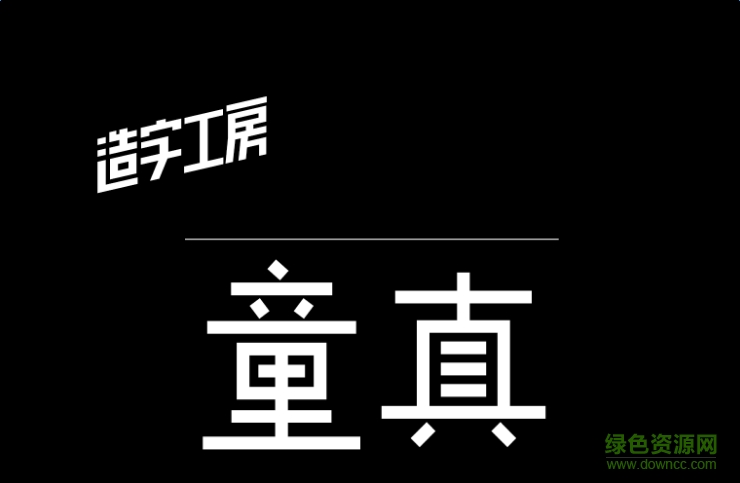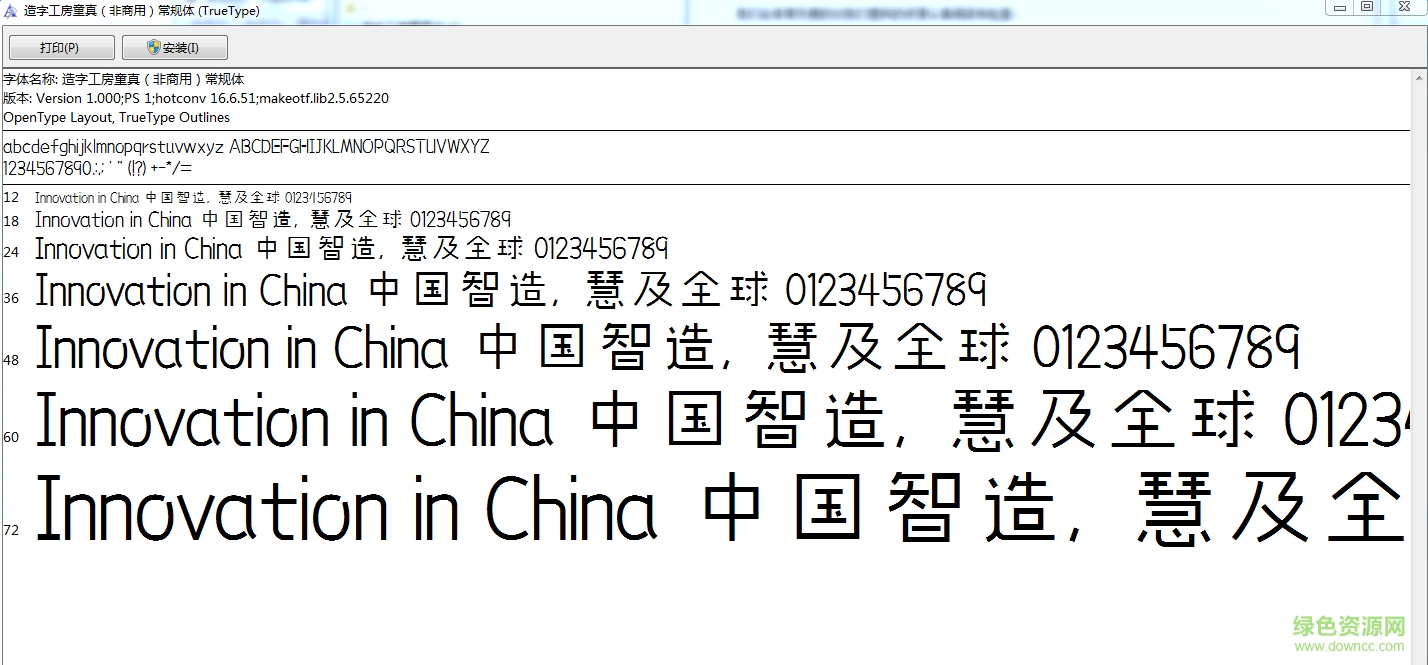
造字工房童真體是一款造字工房類可愛童趣風(fēng)格字體軟件,童真體整體效果無拘無束,非常的滑稽,在兒童讀物設(shè)計(jì)方面有著不錯(cuò)的應(yīng)用,歡迎到綠色資源網(wǎng)下載體驗(yàn),還有更多好看字體盡情期待!
造字工房童真體橫豎筆畫粗細(xì)較為統(tǒng)一,筆畫纖細(xì),娟秀可愛,粗細(xì)勻稱,結(jié)構(gòu)輕巧,特點(diǎn)明確,起落筆及拐角直角設(shè)計(jì),撇捺無多余贅點(diǎn),整體風(fēng)格簡單明了。適用于兒童讀物、報(bào)刊雜志標(biāo)題、廣告設(shè)計(jì)、個(gè)性招牌等視覺環(huán)境,有著極強(qiáng)的應(yīng)用空間。